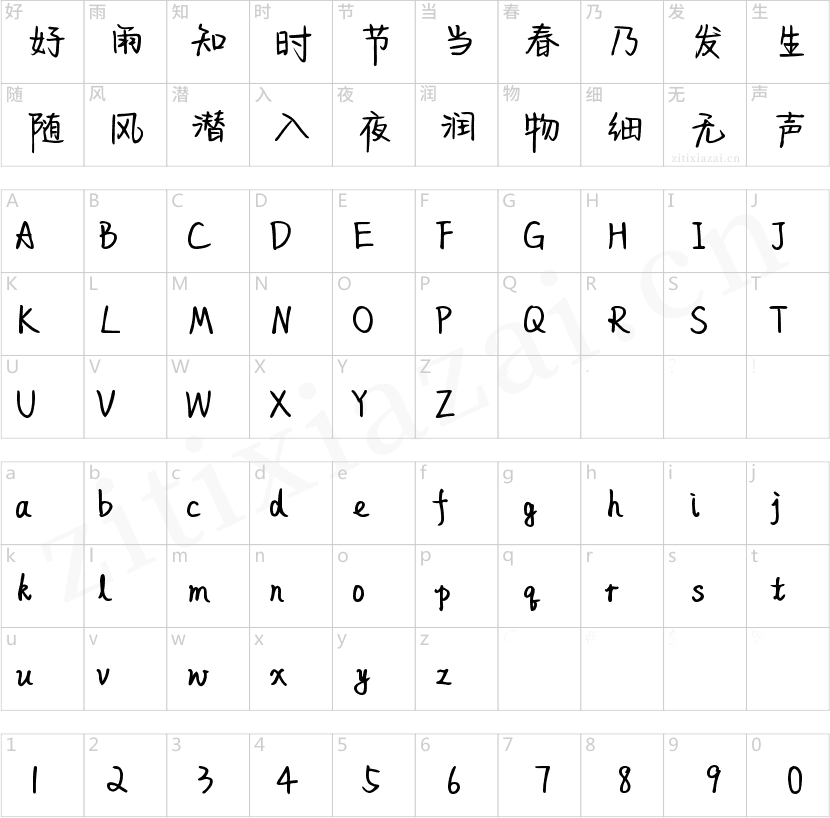
Aa人很奇怪突然相爱,这款字体结构工整、笔画清晰,兼顾美观与易读性,适用于标题、正文、海报、包装、LOGO 等多种场景。字形优雅稳定,风格百搭耐看,适配日常排版与创意设计,让文字呈现更舒适、更具质感。Aa人很奇怪突然相爱一笔一画,皆是细节,以均衡的比例、流畅的线条打造舒适视觉体验,字形端正大气,风格简约现代。无论是商业设计、品牌宣传还是日常排版,都能轻松驾驭,让文字更有格调与力量。Aa人很奇怪突然相爱字体下载。
Aa人很奇怪突然相爱是一款非常具有艺术性的字体,它的设计灵感来源于对古典艺术的研究,同时又融入了现代字体设计的元素。字形优美,笔画粗细变化自然,给人以大气、典雅的感觉。Aa人很奇怪突然相爱是一款既传统又现代的字体,它的设计充满艺术感,美观大方,实用性也非常强。无论是对于设计师还是对于普通读者来说,都是一种非常不错的字体选择。Aa人很奇怪突然相爱适合用于具有艺术感的场合,比如海报、宣传单张、书籍封面等。由于其字形流畅且具有动态感,也适合用于大量的文本排版,如报纸、杂志等。